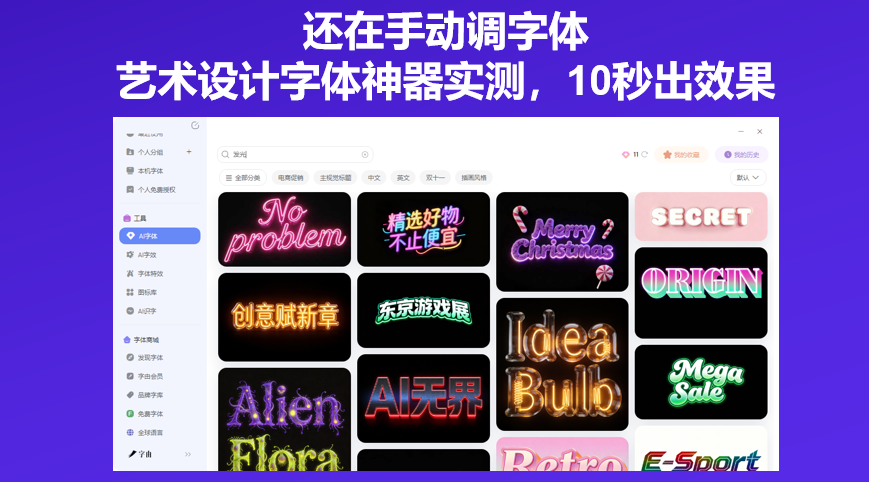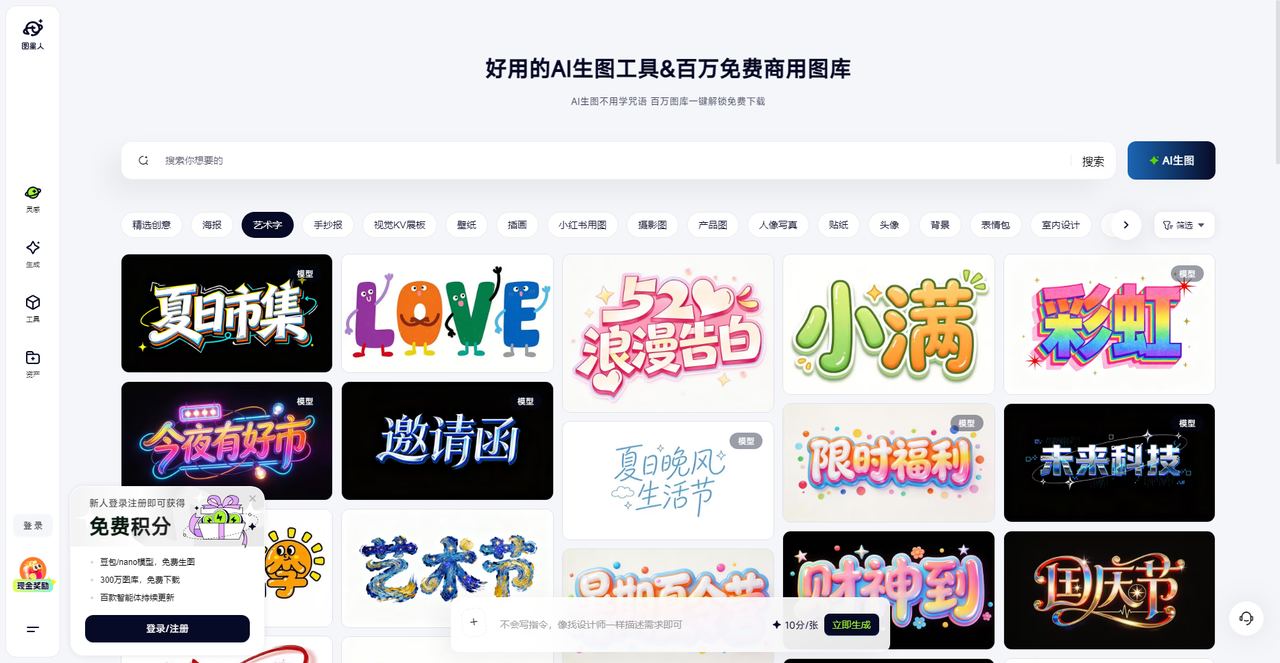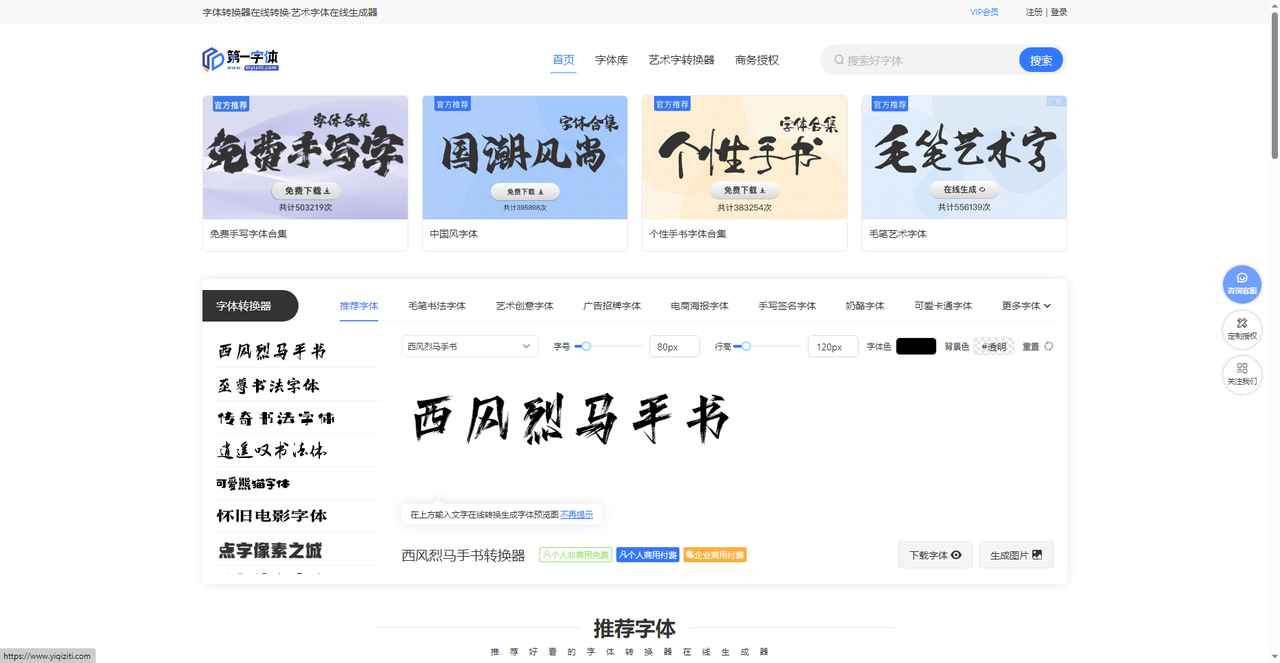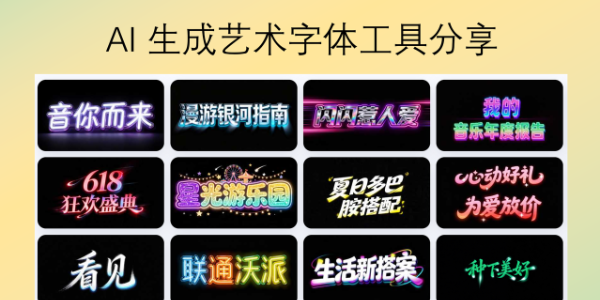
还在手动调字体?艺术设计字体神器实测,10秒出效果
做一张海报标题,在PS里选字体、加发光、调阴影,十几分钟过去了,出来的效果仍然不够满意。其实市面上有不少专门做艺术设计字体的在线工具,可以把普通文字快速转换成各种风格的特效字。本文实测了5款工具,从AI模板一键出图到参数微调,从国潮书法到烫金立体字,覆盖了不同设计场景的需求。不需要设计基础,输入文字即可。
在字由里,聊到“快速出效果”,最直接的功能就是AI字体。它的核心理念很简单:把一个标题字从零开始“设计”的时间,压缩成从一堆选项里“选择”的时间-。
这个功能和传统方法最大的不同,在于它极度简化的操作路径。用户不再需要打开Photoshop,从新建画布开始,经历找字体、调字号、加特效、排版等一系列步骤。在字由AI字体里,这套复杂的流程被简化成三步:
- 选风格:打开AI字体模块,你会看到一排按“国潮风”、“霓虹灯”、“金属质感”、“电商促销”等场景分类好的标签-。
- 换文字:在模板的预览图里,把示例文字改成你自己的标题。
- 点击生成:点一下按钮,等个15到20秒,一张直接能用的PNG图片就出来了-。
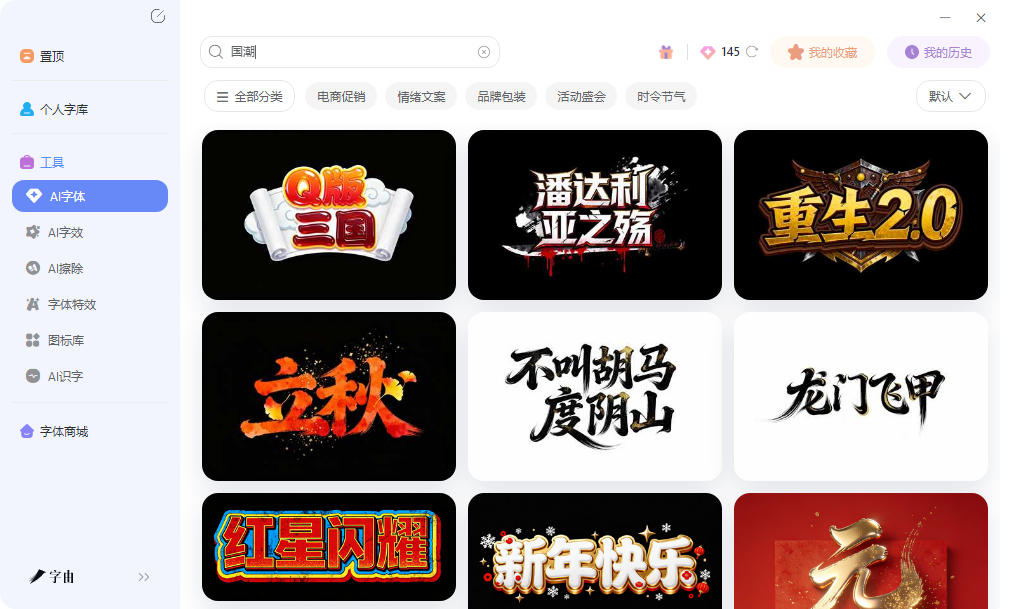
这种“工业化输入-输出”逻辑的精髓在于,它将过往可能需要花几十分钟去构思和打磨的参数,全部由AI提前计算并封装好了。这意味着,无论是做国潮海报还是科技感封面,你都不需要了解复杂的图层样式,甚至连字体都不用自己选。你的核心工作不再是技术性的“制作”,而是创意性的“判断”——判断哪个预制模板的氛围,最贴合你想要表达的感觉。这等于把字体设计的前半段工作(找参考、定风格、试搭配)外包给了AI。
在你确认风格后,输出的结果质量是稳定且可预期的。在5.0版本及之后的更新中,字由还优化了加载和生成性能-,并整合了AI助手与DeepSeek来辅助决策,进一步提升了整个流程的流畅度。
2、图星人
图星人是一个AI生图与素材图库平台。用户在搜索框输入关键词,如国潮端午海报或3D艺术字,平台会从图库中检索相关素材,或通过豆包、nano等模型生成新的艺术字图片。平台提供海报、插画、艺术字、手抄报等多种类型的素材,支持在线编辑文字后下载。
用户还可以使用平台的AI生图功能,通过简单的描述生成带有艺术字效果的海报背景,再叠加文字排版。图星人的图库累计超过300万张,其中艺术字类素材按照场景分类,包括电商促销、节日节气、行业专用等,适合快速找到成品模板直接使用。
3、第一字体网
第一字体网提供艺术字体在线转换功能。用户输入文字后,可以从毛笔书法、艺术创意、广告招牌、电商海报、手写签名等分类中选择字体。
页面右侧展示了多个热门字体转换器入口,包括西风烈马手书、传奇书法字铺、逍遥双书法体、可爱熊猫字体、怀旧电影字体等。用户点击任意字体进入转换页面,可以调节字号、行高、字体色、背景色,支持透明背景。转换结果分为个人非商用免费、个人商用付费、企业商用付费三种授权方式,用户可以根据自己的使用场景选择。点击生成图片即可预览并下载。该网站还提供了字体下载入口,用户可以下载字体文件到本地安装使用。
4、字笑
字笑是一个在线艺术字体设计平台。用户进入页面后,可以在画布上添加文案,从右侧的字效模板库中选择喜欢的风格。字效模板按用途分类,包括热门、电商、可爱、潮酷、炫彩、复古、烫金等。字效类型包括基础、描边、叠层、渐变、立体、纹理等。用户选择一个模板后,点击应用,文案会实时显示对应的效果。画布支持拖拽调整文字位置,也可以添加多个文字图层进行组合设计。
完成编辑后,点击下载高清PNG按钮即可保存。登录后可下载无水印大图,免费版有水印限制。字笑还提供了云字体功能,用户可以将自己常用的字体上传到云端,在不同设备上同步使用。
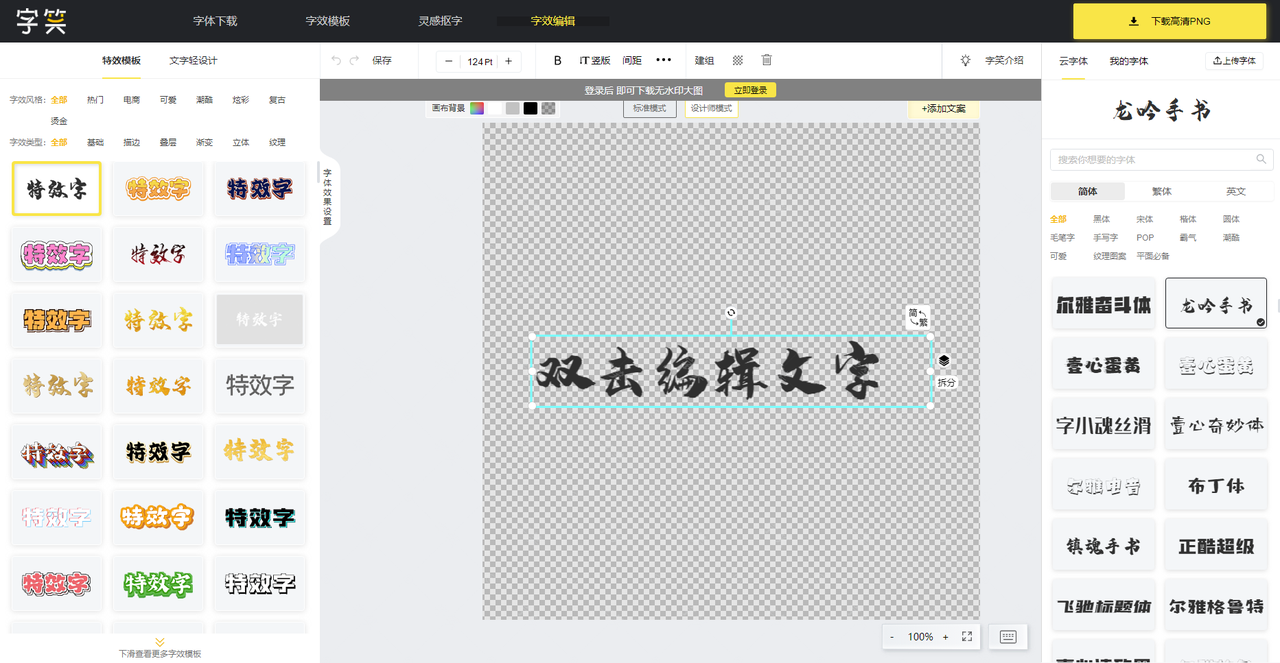
5、美术字
美术字是一个文字特效在线编辑平台,功能参数调节非常细致。用户输入文字后,可以在左侧选择字体类型,包括经典字体、艺术字体、花体字体、POP体、艺术英文、毛笔字体、篆书字体等。右侧面板可以调节字体大小、字体颜色、背景宽度、背景高度、背景透明开关、填充纹理、背景纹理、背景颜色、渐变方向、横向间距、纵向间距等。同时支持加粗、倾斜、下划线、中划线、左对齐、右对齐、竖排、翻转、复制、删除、渐变、加色等文字样式操作。
用户可以在画布上添加多个文字图层,每个图层独立编辑。页面还提供了模板中心,用户可以直接套用预设的特效模板,包括最新、热门、下载量排序的模板。编辑完成后点击保存图片即可下载。美木字适合需要精细控制每一个设计参数的用户,功能接近简化版PS但操作更直观。
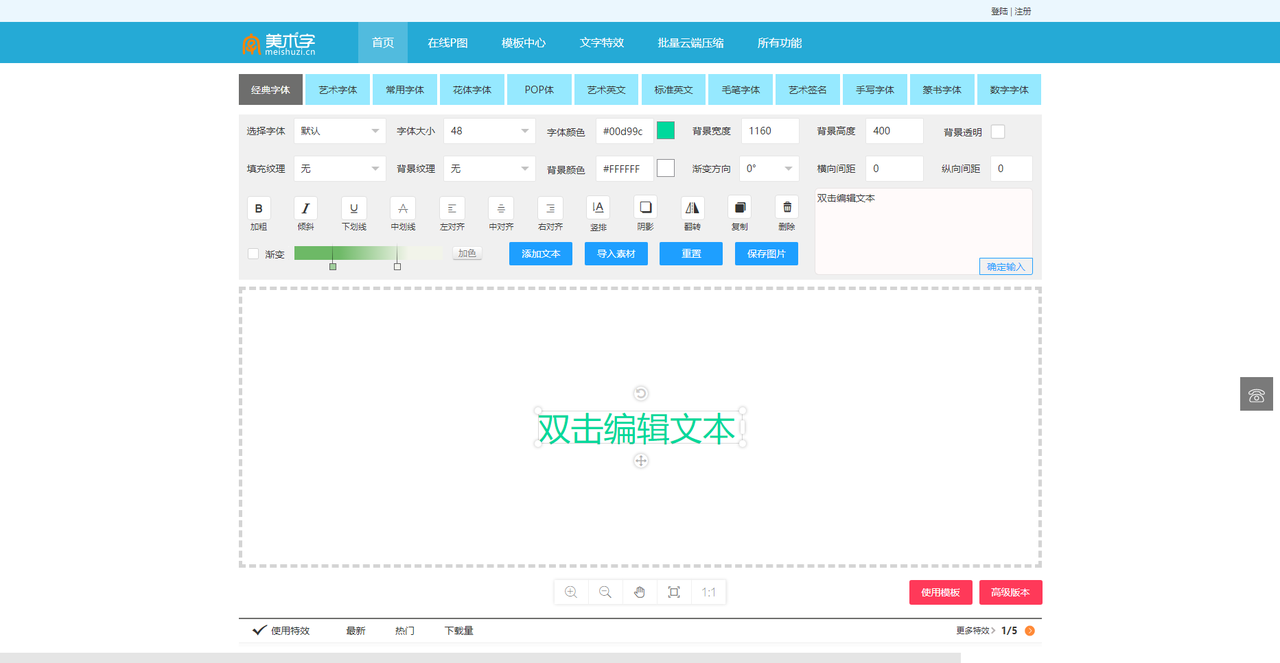
艺术设计字体工具大致分两类。字由属于AI预制模板型,多套模板覆盖国潮、霓虹、金属等主流风格,用户只需要替换文案,不需要自己调参数,适合时间紧或没有设计基础的场景。图星人侧重素材库检索和AI生图,适合需要成品模板和背景图融合的场景。第一字体网提供多种书法和创意字体在线转换,授权分级清晰。字笑提供模板化字效应用,支持多图层组合。美木字参数调节最细致,适合愿意花时间精细调整的用户。根据手头的项目类型和时间预算选一个工具,几分钟就能拿到结果。